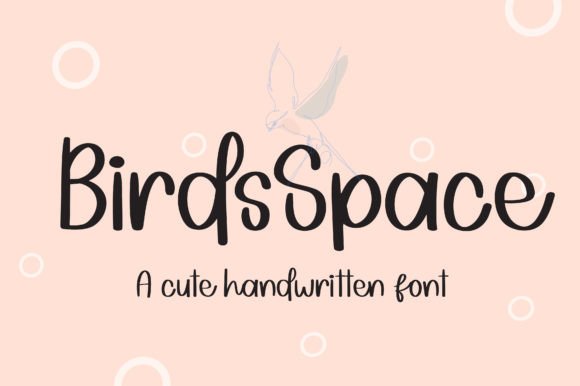
Birdsspace
Encontrar os elementos de design certos pode ser um desafio, mas Birdsspace oferece uma coleção excepcional que eleva o seu trabalho instantaneamente.
Trabalhado com precisão, Birdsspace fornece vetores limpos, tipografia suave e uma licença comercial para sua tranquilidade.
Quer você esteja criando produtos POD (Print on Demand), convites de casamento ou gráficos para mídias sociais, Birdsspace é a escolha ideal.